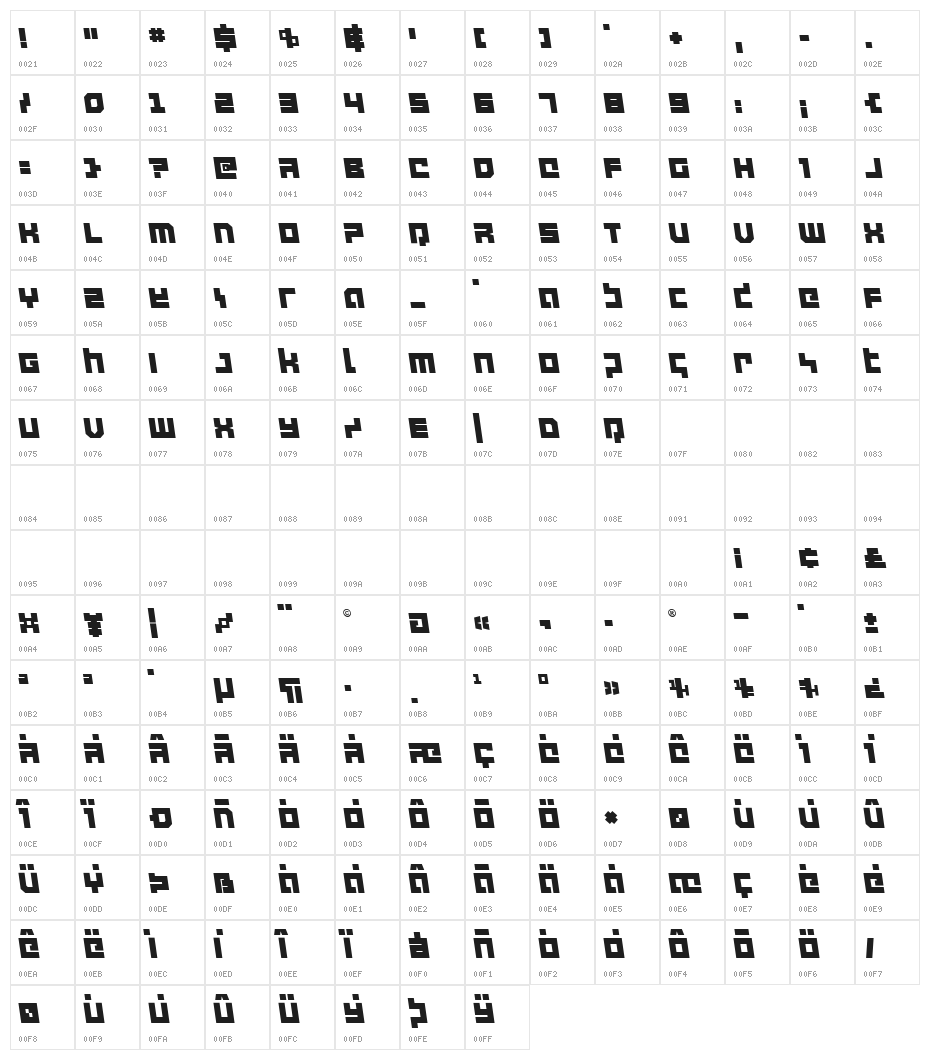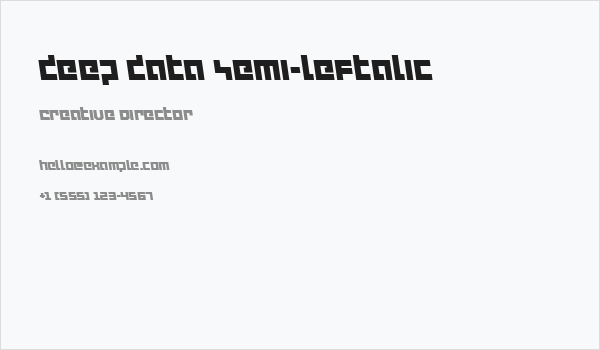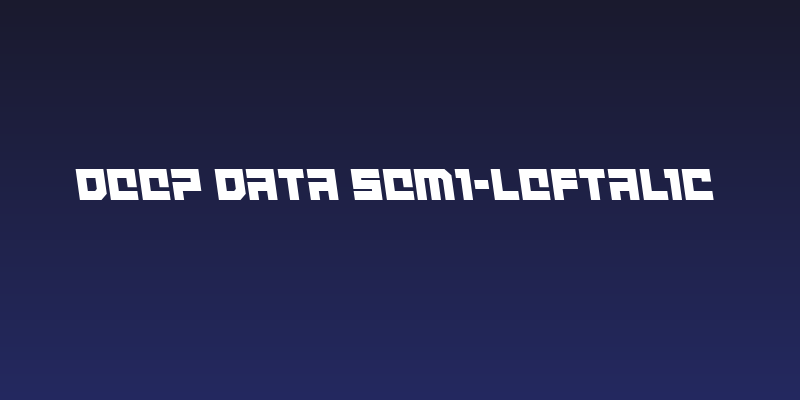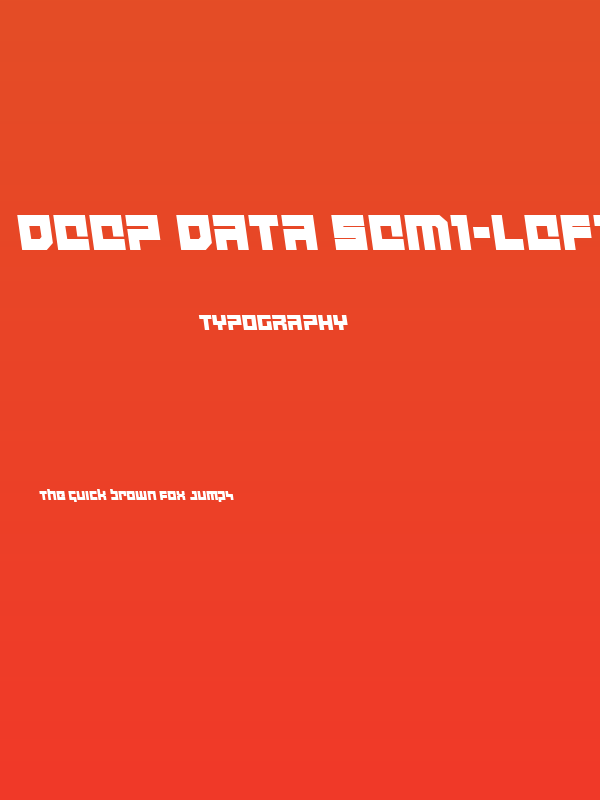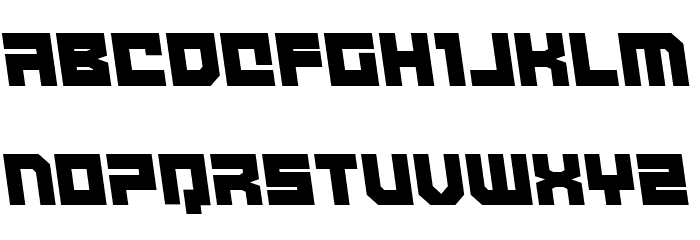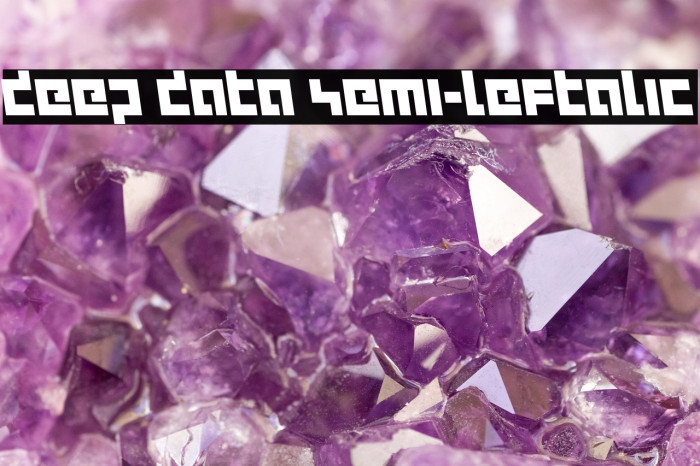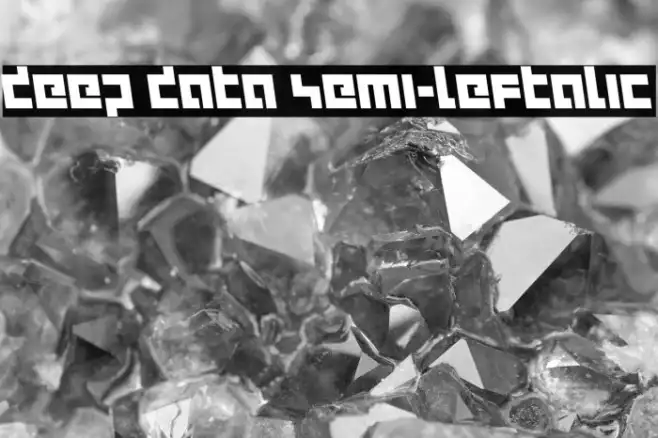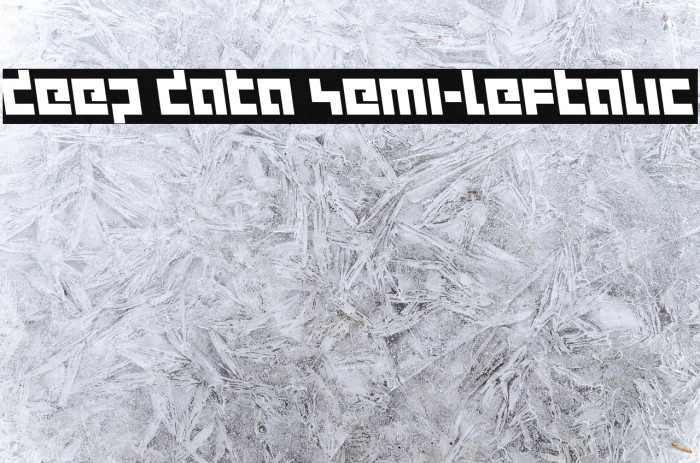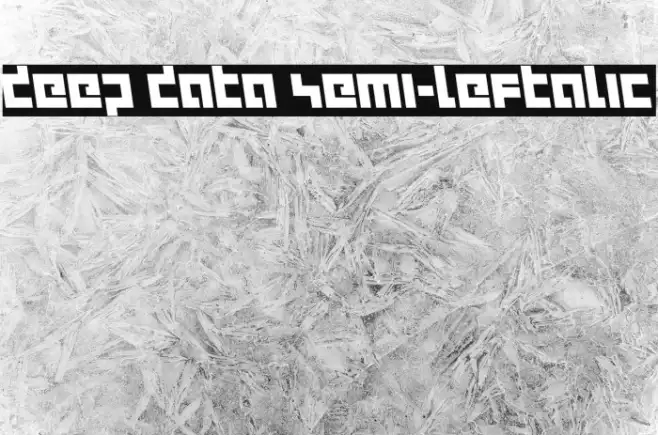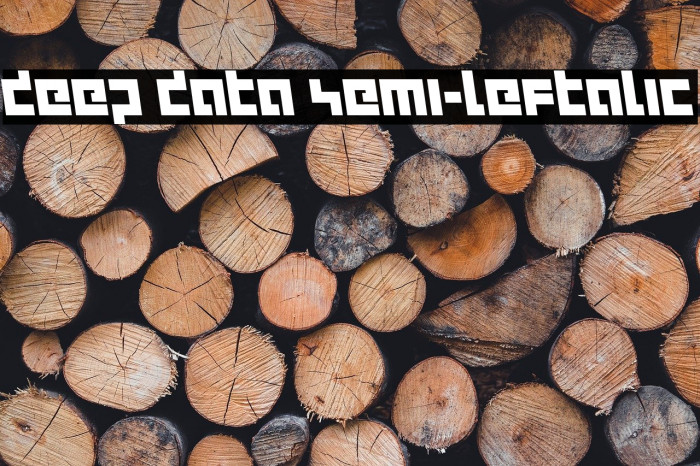
deep data semi-leftalic Font
✎ Futuristic
| Vorgeschlagene Projekte | Ideal for tech-related branding, video game titles, digital art projects, and modern posters. |